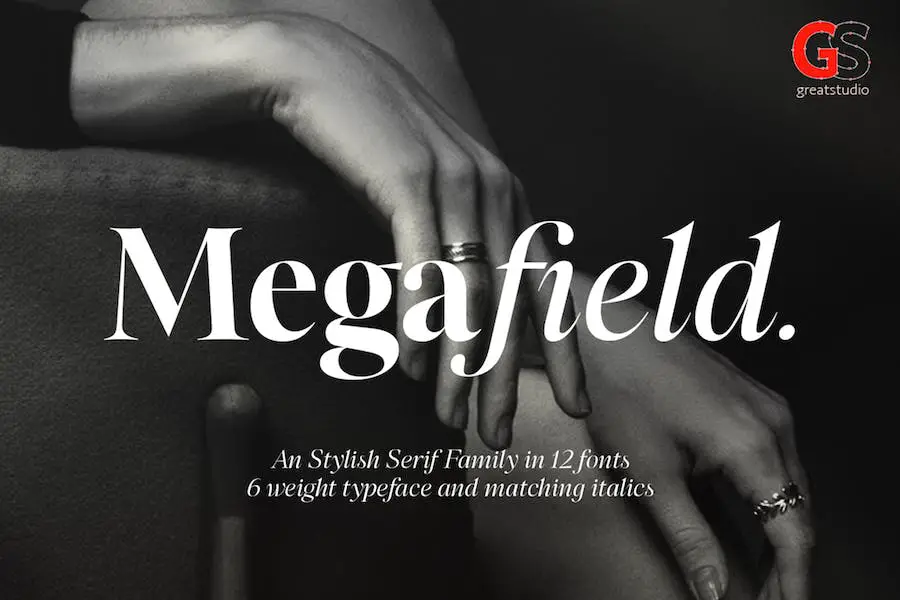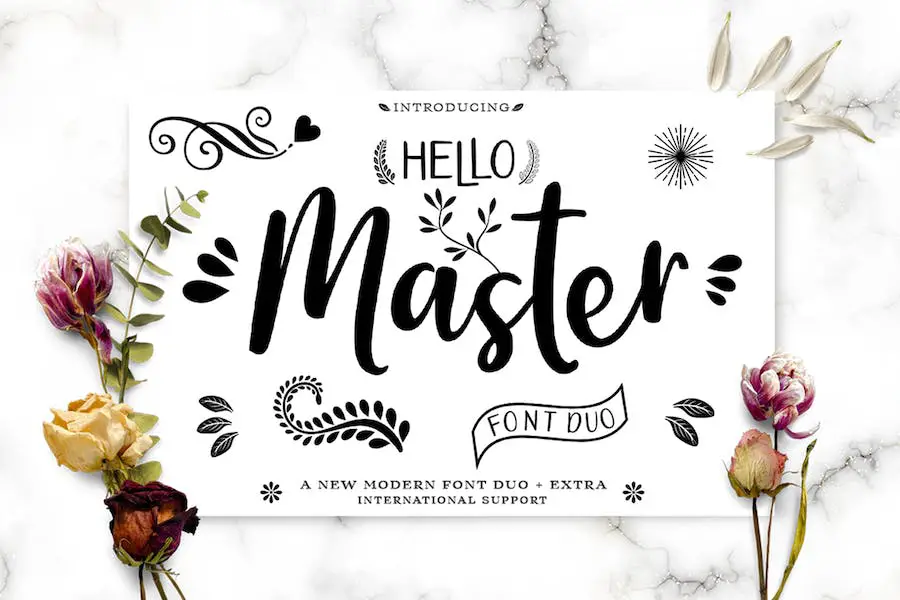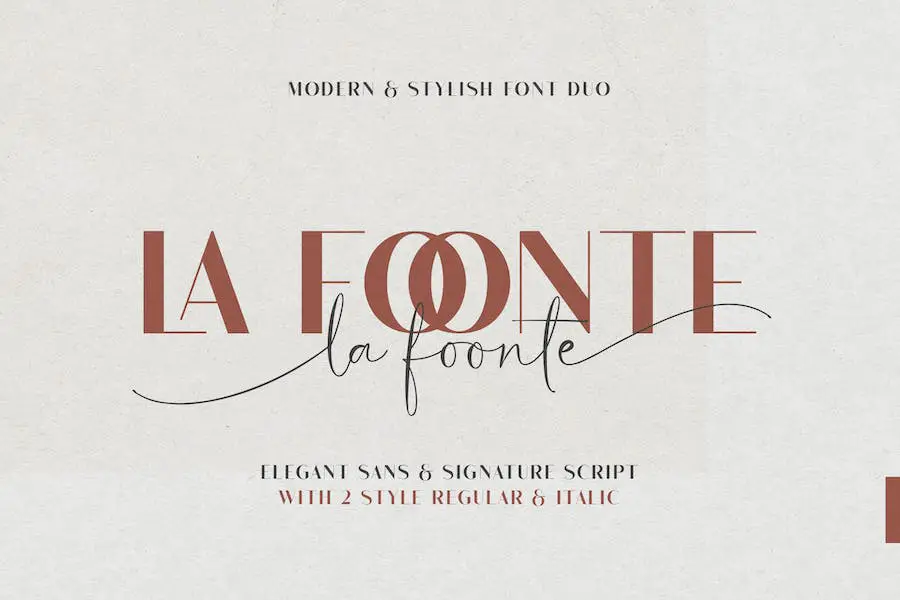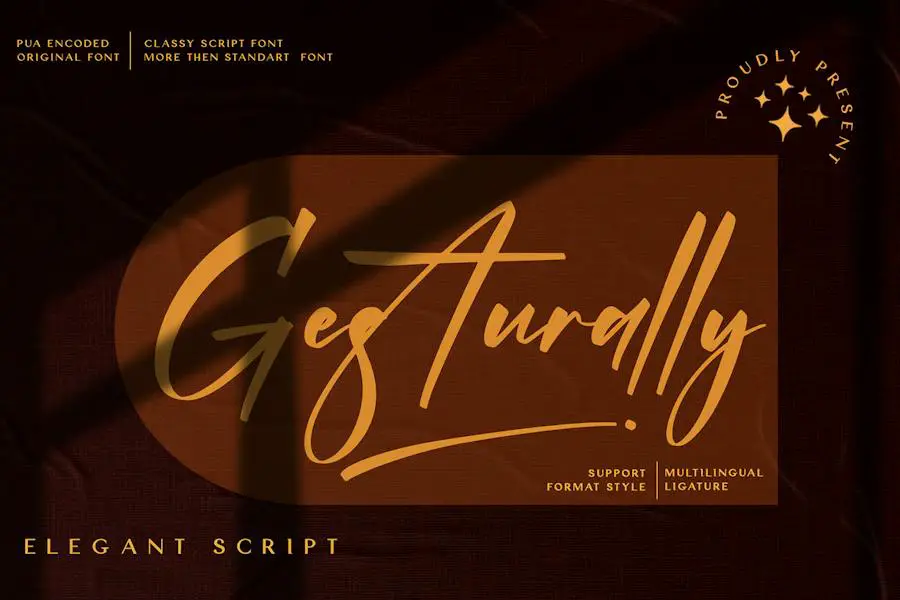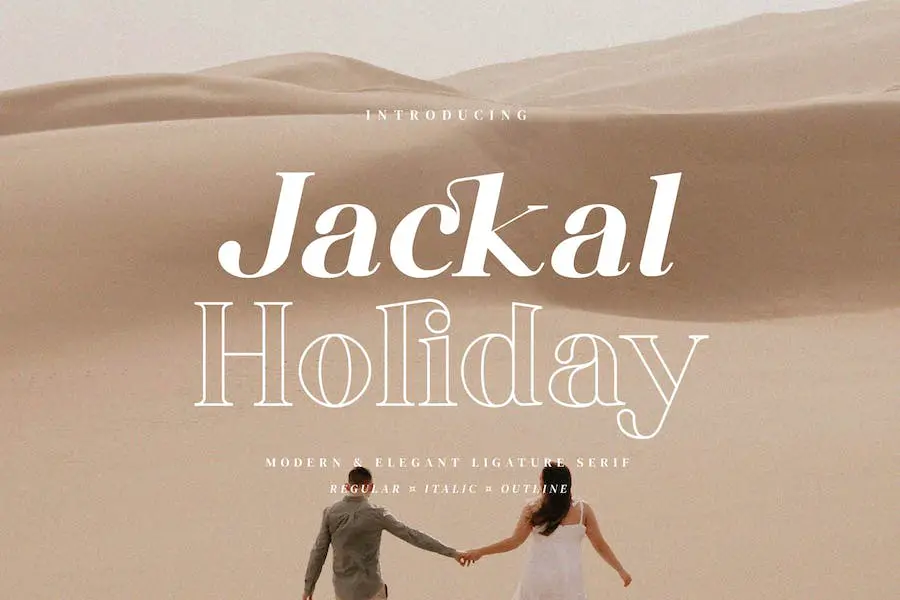
15 แบบอักษรขอบคุณที่ดีที่สุดในปี 2023 (ฟรีและพรีเมียม)
เผยแพร่แล้ว: 2023-12-04คุณเป็นนักออกแบบกราฟิกที่มีภารกิจในการค้นหาแบบอักษรขอบคุณที่สมบูรณ์แบบเพื่อปรับปรุงการออกแบบโครงการของคุณหรือไม่? ไม่ต้องมองอีกต่อไป! ในบล็อกโพสต์นี้ เราได้รวบรวมคอลเลกชันแบบอักษรขอบคุณที่ดีที่สุดที่คัดสรรมาเป็นอย่างดี
ไม่ว่าคุณจะออกแบบโลโก้ การ์ดอวยพร หรือการออกแบบอื่นๆ ที่ต้องแสดงความขอบคุณ แบบอักษรเหล่านี้จะช่วยยกระดับงานของคุณไปอีกระดับ
ตอนนี้ คุณอาจสงสัยว่าเหตุใดการเลือกแบบอักษรจึงมีความสำคัญในการแสดงความขอบคุณ การศึกษาพบว่าการพิมพ์มีผลกระทบอย่างมากต่อวิธีที่ผู้อ่านตีความและมีส่วนร่วมกับข้อความ
ในความเป็นจริง แบบอักษรที่แตกต่างกันสามารถทำให้เกิดอารมณ์ที่แตกต่างกันและสื่อถึงความจริงใจในระดับที่แตกต่างกัน ดังนั้น เมื่อต้องการกล่าวขอบคุณ ทำไมไม่เลือกแบบอักษรที่ไม่เพียงแต่ดูน่าดึงดูดใจ แต่ยังโดนใจผู้ชมของคุณด้วย
ในบทความนี้ เราจะสำรวจแบบอักษรขอบคุณหลากหลายรูปแบบที่ทำให้เกิดความสมดุลที่สมบูรณ์แบบระหว่างความสง่างามและความชัดเจน ตั้งแต่เซอริฟคลาสสิกไปจนถึงซานเซอริฟสมัยใหม่ เราจะครอบคลุมแบบอักษรที่หลากหลาย มีสไตล์ และเหมาะสำหรับการออกแบบที่หลากหลาย
ดังนั้น เพื่อเป็นการไม่ให้เสียเวลา เรามาเจาะลึกตัวเลือกอันดับต้นๆ ของเราและค้นพบแบบอักษรขอบคุณที่สมบูรณ์แบบเพื่อทำให้โปรเจ็กต์ของคุณโดดเด่น เริ่มต้นความกตัญญู!
แบบอักษรขอบคุณระดับพรีเมียมที่ดีที่สุด
กำลังมองหาการยกระดับเกมการออกแบบของคุณอยู่ใช่ไหม? ไม่ต้องมองไปไกลกว่าแบบอักษรขอบคุณระดับพรีเมียมเหล่านี้ ด้วยการออกแบบที่มีสไตล์และเป็นเอกลักษณ์ มั่นใจได้ว่าจะเพิ่มสัมผัสพิเศษของความซับซ้อนและความสง่างามให้กับโครงการของคุณ อย่าพลาดการสำรวจแบบอักษรที่ต้องมีเหล่านี้สำหรับความพยายามในการออกแบบครั้งต่อไปของคุณ!
เกษตรลิก
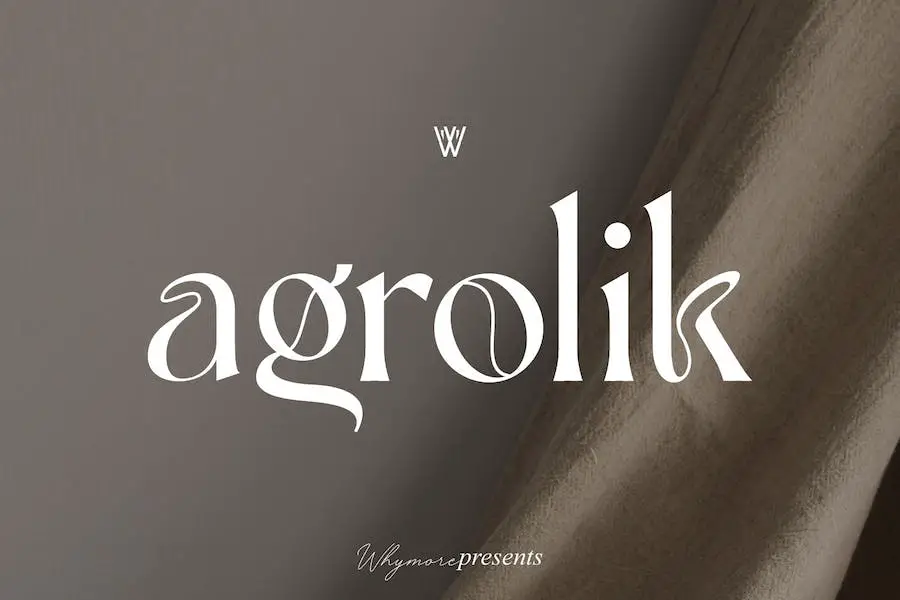
agrolik เป็นแบบอักษรที่ยอดเยี่ยมในการปรับปรุงโครงการของคุณด้วยรูปทรงที่มีเอกลักษณ์และสร้างสรรค์ มันผสมผสานกับแบบอักษร serif ได้อย่างราบรื่น ทำให้เป็นตัวเลือกที่สมบูรณ์แบบสำหรับนักออกแบบกราฟิกที่ต้องการเพิ่มความคิดสร้างสรรค์ให้กับการออกแบบของพวกเขา
คุณสมบัติหลักประการหนึ่งของ agrolik คือความสามารถในการปรับเปลี่ยนรูปทรงของตัวอักษรแต่ละตัว ส่งผลให้มีการออกแบบที่โดดเด่นและสะดุดตาอย่างแท้จริง ไม่ว่าคุณจะทำงานเกี่ยวกับโลโก้ เว็บไซต์ หรือโปรเจ็กต์การออกแบบอื่นๆ แบบอักษรนี้จะช่วยให้คุณโดดเด่นจากคนอื่นๆ
ด้วย agrolik คุณสามารถปลดปล่อยความคิดสร้างสรรค์และทดลองกับรูปแบบตัวอักษรและรูปร่างต่างๆ ปรัชญาพื้นฐานของมันคือการจัดลำดับความสำคัญของความคิดสร้างสรรค์ ช่วยให้คุณสามารถสำรวจความเป็นไปได้ที่ไม่มีที่สิ้นสุดและนำความคิดของคุณมาสู่ความเป็นจริง
แฟนตาซีเคลิโรล
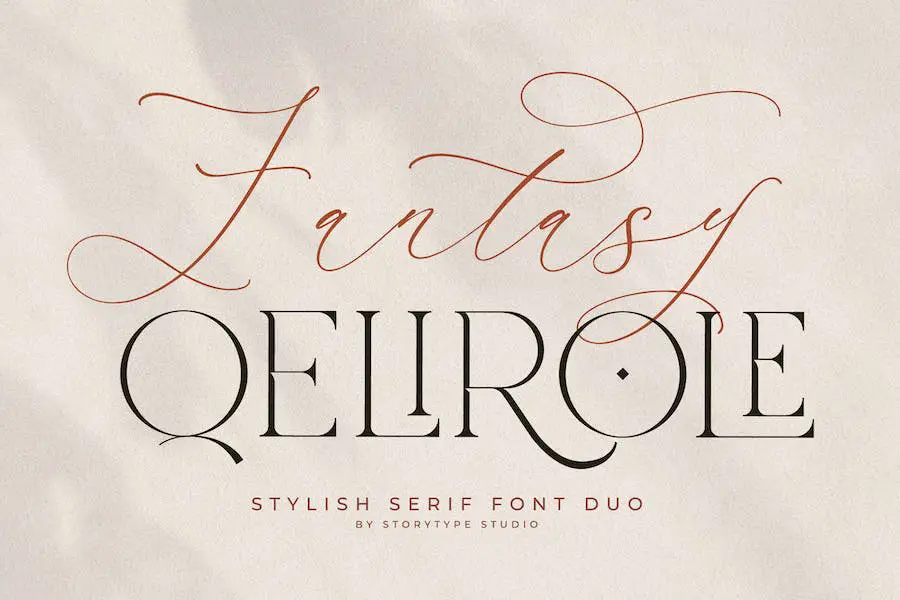
Fantasy Qelirole เป็นแบบอักษรอเนกประสงค์ที่สามารถยกระดับโปรเจ็กต์สร้างสรรค์ดิจิทัลและสิ่งพิมพ์ของคุณได้อย่างมาก ด้วยการออกแบบและสไตล์ที่เป็นเอกลักษณ์ จึงมั่นใจได้ว่าจะดึงดูดความสนใจจากผู้ชมและเพิ่มความสง่างามให้กับงานของคุณ
ไม่ว่าคุณจะออกแบบโลโก้ สร้างโปสเตอร์ หรือสร้างบัตรเชิญที่สวยงาม แบบอักษรนี้เป็นตัวเลือกที่สมบูรณ์แบบเพื่อเสริมผลิตภัณฑ์สร้างสรรค์ของคุณ
สิ่งแรกที่คุณจะสังเกตเห็นเกี่ยวกับ Fantasy Qelirole คือรูปลักษณ์ที่โดดเด่น ด้วยเส้นสายที่สลับซับซ้อนและเส้นโค้งที่ละเอียดอ่อน ช่วยเพิ่มความรู้สึกหรูหราและสวยงามให้กับทุกโครงการ
ไม่ว่าคุณจะมองหารูปลักษณ์แนววินเทจ ทันสมัย หรือสนุกสนาน แบบอักษรนี้สามารถปรับให้เหมาะกับความต้องการของคุณได้
บ้านนก
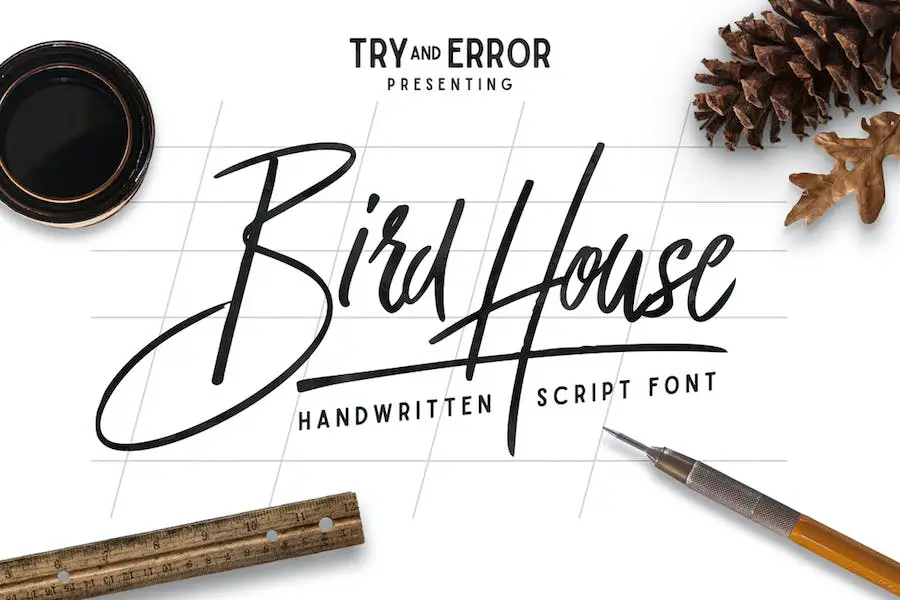
Bird House เป็นแบบอักษรที่เขียนด้วยลายมือชื่อ 'It Script' ซึ่งได้รับการออกแบบอย่างสวยงามโดยใช้ปากกามาร์กเกอร์ แบบอักษรนี้เพิ่มสัมผัสที่มีเอกลักษณ์และเป็นศิลปะให้กับทุกโครงการ ทำให้เหมาะสำหรับนักออกแบบกราฟิกที่ต้องการปรับปรุงการออกแบบของตน
ด้วยความรู้สึกแบบงานฝีมือ Bird House มอบกลิ่นอายที่เป็นส่วนตัวและแท้จริงให้กับงานของคุณ ทำให้มันโดดเด่นจากฝูงชน
คุณลักษณะของ Bird House ได้แก่ ลายเส้นที่สนุกสนานและเป็นธรรมชาติ ซึ่งสร้างรูปลักษณ์ที่เป็นธรรมชาติและเห็นอกเห็นใจ การใช้มาร์กเกอร์ในการสร้างแบบอักษรจะทำให้แบบอักษรมีพื้นผิวที่ดูไม่สมบูรณ์ ช่วยเพิ่มคุณลักษณะและเสน่ห์ให้กับการออกแบบของคุณ
สไตล์การเขียนด้วยลายมือช่วยเพิ่มความอบอุ่นและบุคลิกภาพ ทำให้เหมาะสำหรับโปรเจ็กต์ที่ต้องการความเป็นส่วนตัว
จินดอม
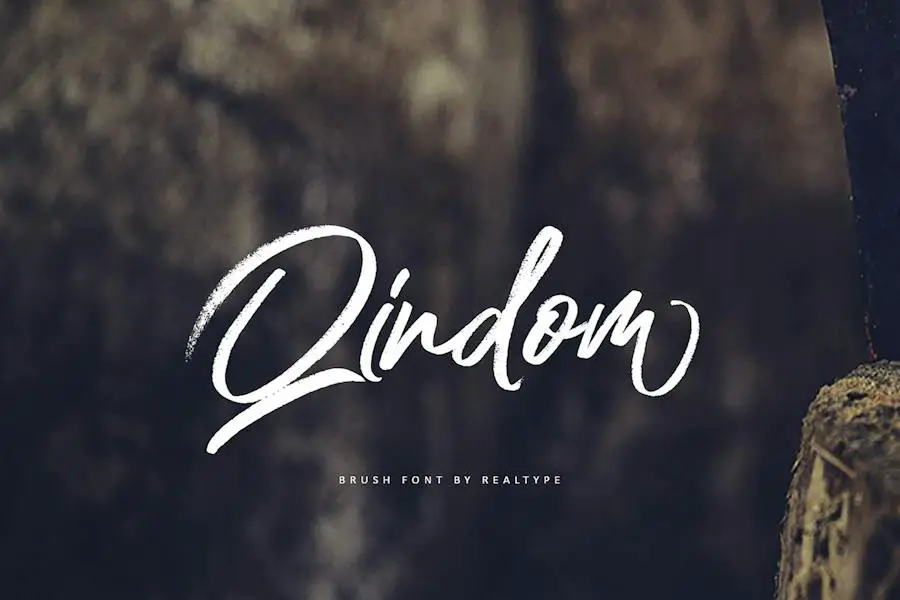
Qindom เป็นแบบอักษรที่เป็นเอกลักษณ์ซึ่งได้รับแรงบันดาลใจจากความสวยงามและความลื่นไหลของฝีแปรงที่เป็นธรรมชาติ ด้วยการออกแบบที่หรูหราและมีเอกลักษณ์ แบบอักษรนี้จึงเหมาะสำหรับนักออกแบบกราฟิกที่ต้องการเพิ่มความน่าดึงดูดทางสายตาให้กับโปรเจ็กต์ของตน
แบบอักษรนี้ให้ความรู้สึกเป็นธรรมชาติและเป็นธรรมชาติ ทำให้การออกแบบของคุณให้ความรู้สึกอบอุ่นและสมจริง ลายเส้นที่เหมือนพู่กันสร้างลุคแบบงานฝีมือ โดยเพิ่มสัมผัสเฉพาะตัวให้กับทุกสิ่งที่คุณสร้างสรรค์
ไม่ว่าคุณจะออกแบบโลโก้ โปสเตอร์ หรือเว็บไซต์ Qindom จะนำสัมผัสแห่งศิลปะมาสู่งานของคุณ
คุณลักษณะของแบบอักษรนี้คือสิ่งที่ทำให้มันแตกต่างอย่างแท้จริง ฝีแปรงที่สลับซับซ้อนได้รับการสร้างสรรค์ขึ้นอย่างพิถีพิถันเพื่อเลียนแบบพื้นผิวและการเคลื่อนไหวของแปรงจริง ดูเหมือนว่าตัวอักษรแต่ละตัวจะไหลไปสู่ตัวอักษรถัดไปได้อย่างง่ายดาย ทำให้เกิดความรู้สึกถึงความกลมกลืนและจังหวะ
ออกเดทประวัติศาสตร์
Dating Historia เป็นตระกูลฟอนต์อเนกประสงค์ที่มีทั้งเวอร์ชันปกติและตัวเอียง ให้คุณเลือกได้ทั้งหมดแปดประเภท ด้วยตัวเลือกที่หลากหลาย แบบอักษรนี้จึงเหมาะสำหรับนักออกแบบกราฟิกที่ต้องการปรับปรุงการออกแบบโครงการของตน
ตระกูลฟอนต์นี้มีหลากหลายสไตล์ให้คุณทดลองใช้ ช่วยให้คุณค้นหาแบบที่ลงตัวกับโปรเจ็กต์ของคุณได้ ไม่ว่าคุณจะทำงานบนเว็บไซต์ โลโก้ หรือใบปลิวส่งเสริมการขาย Dating Historia มีความสามารถรอบด้านในการปรับให้เข้ากับการออกแบบใดๆ